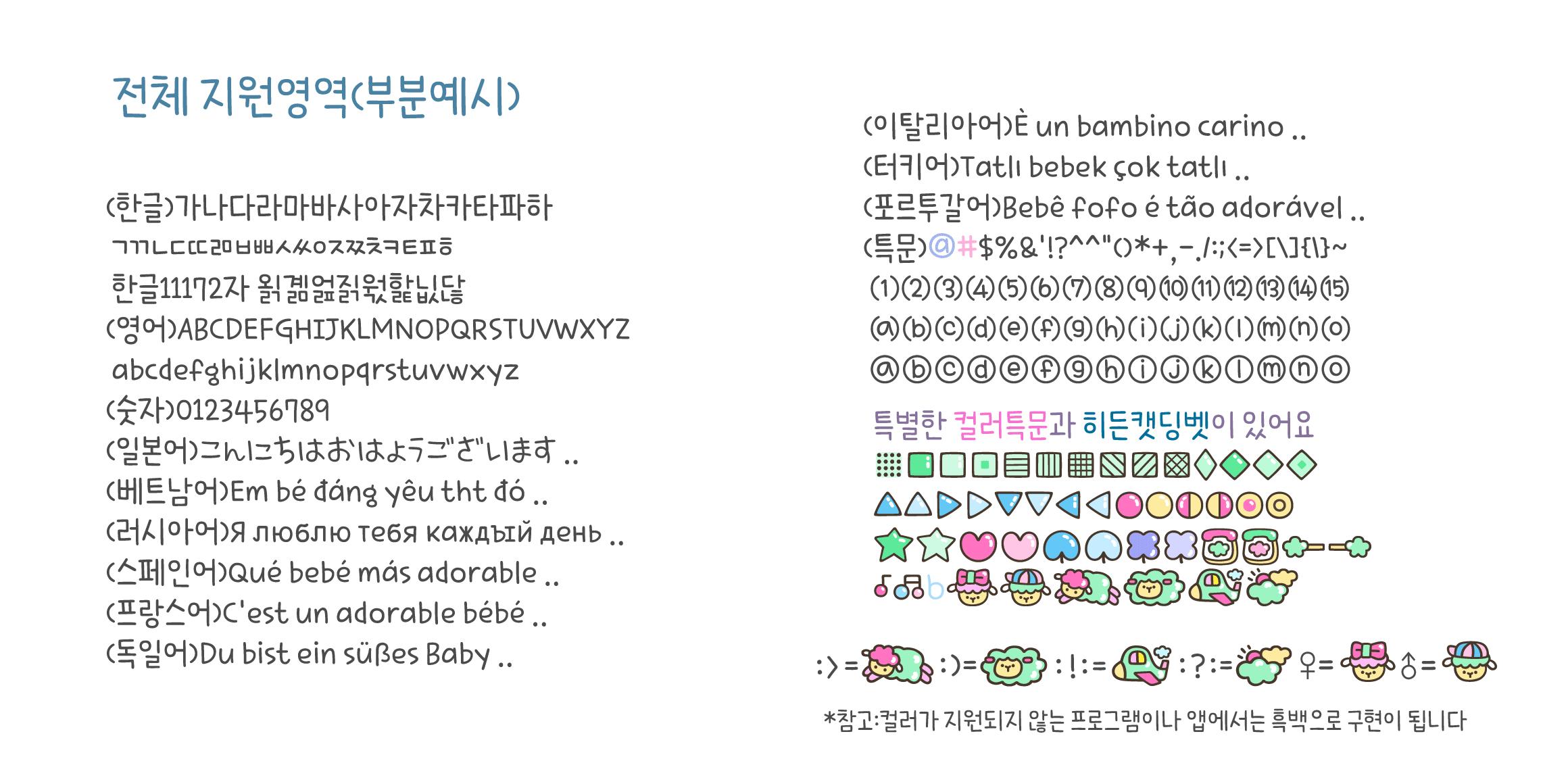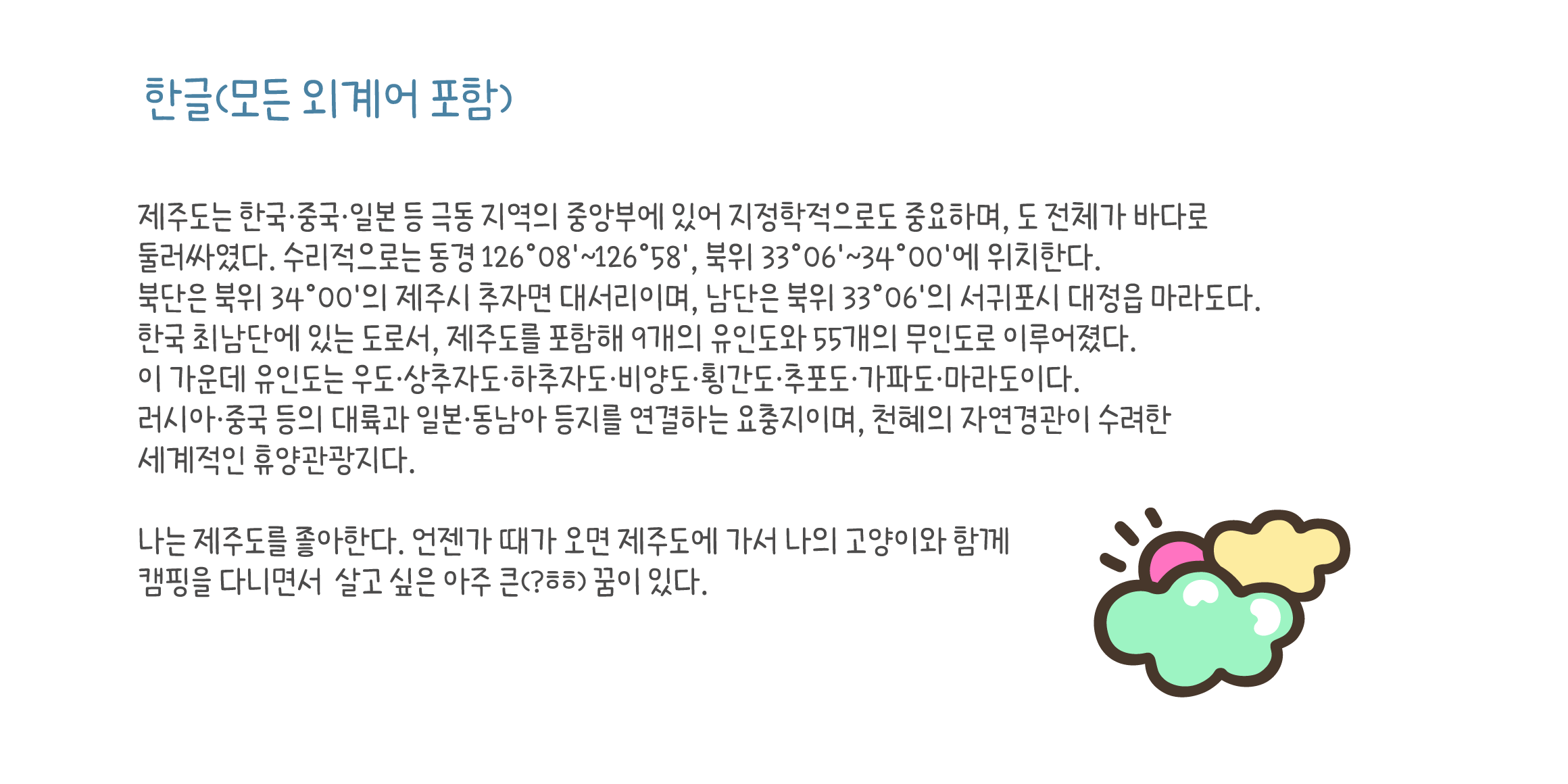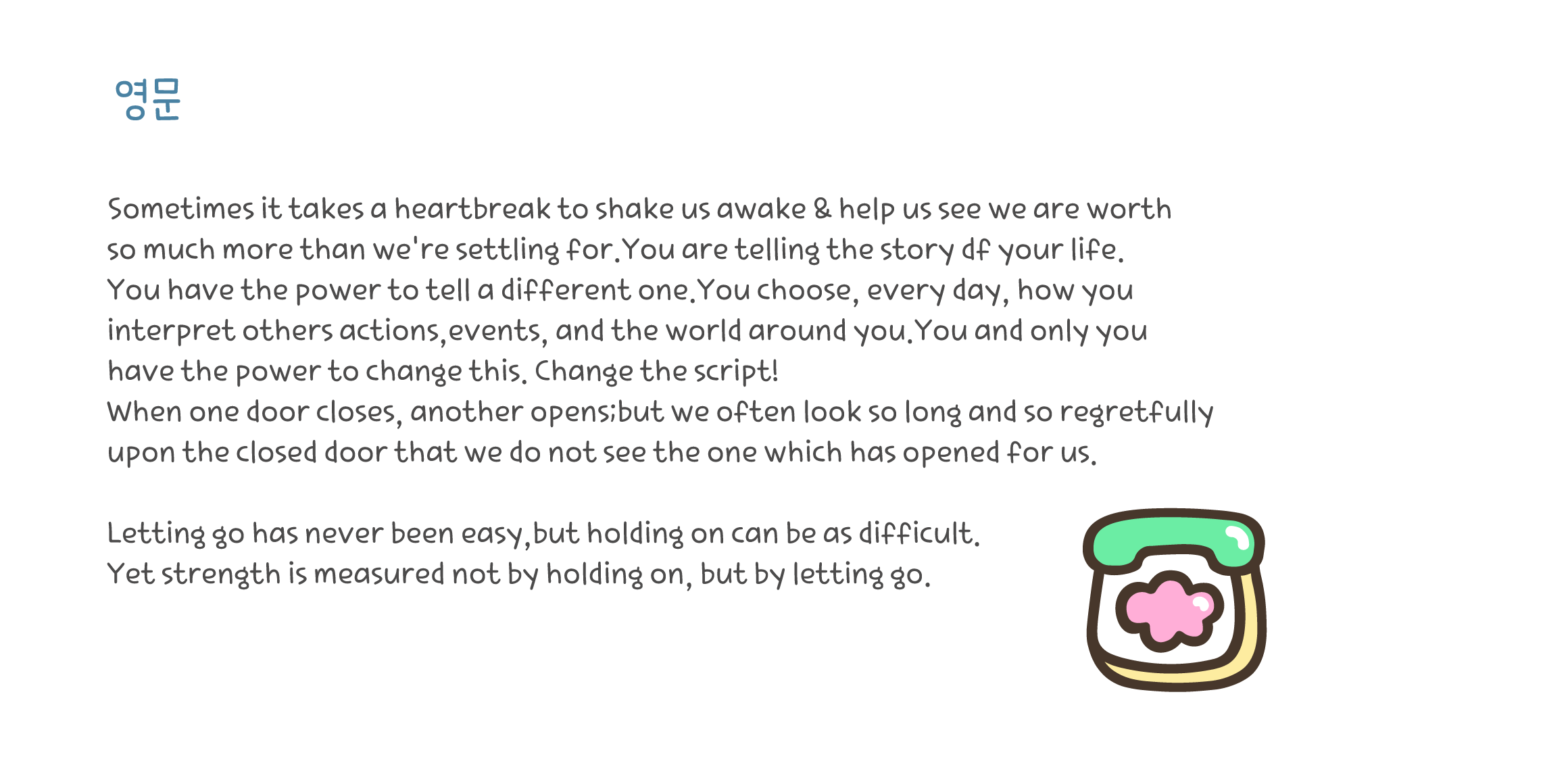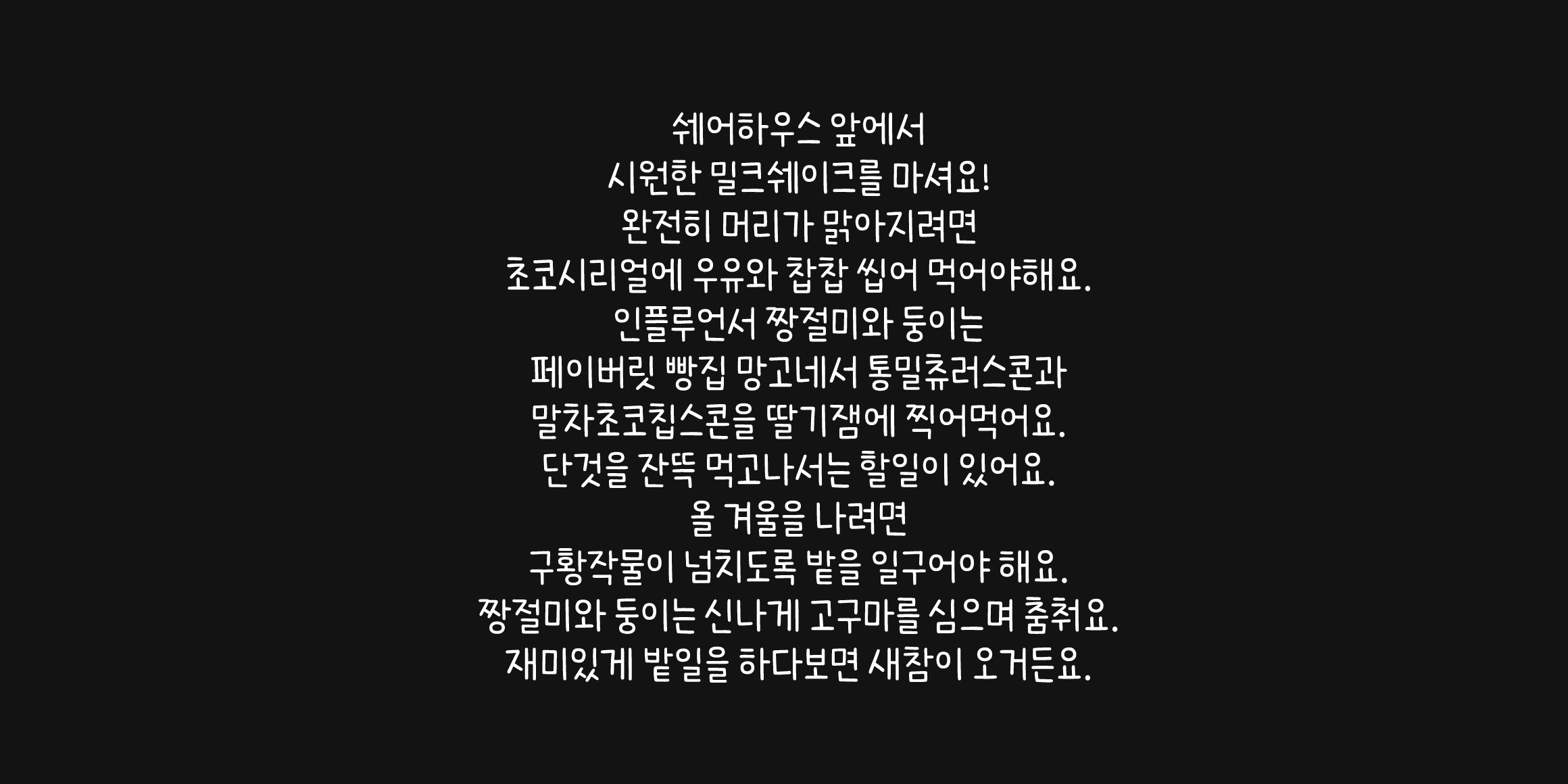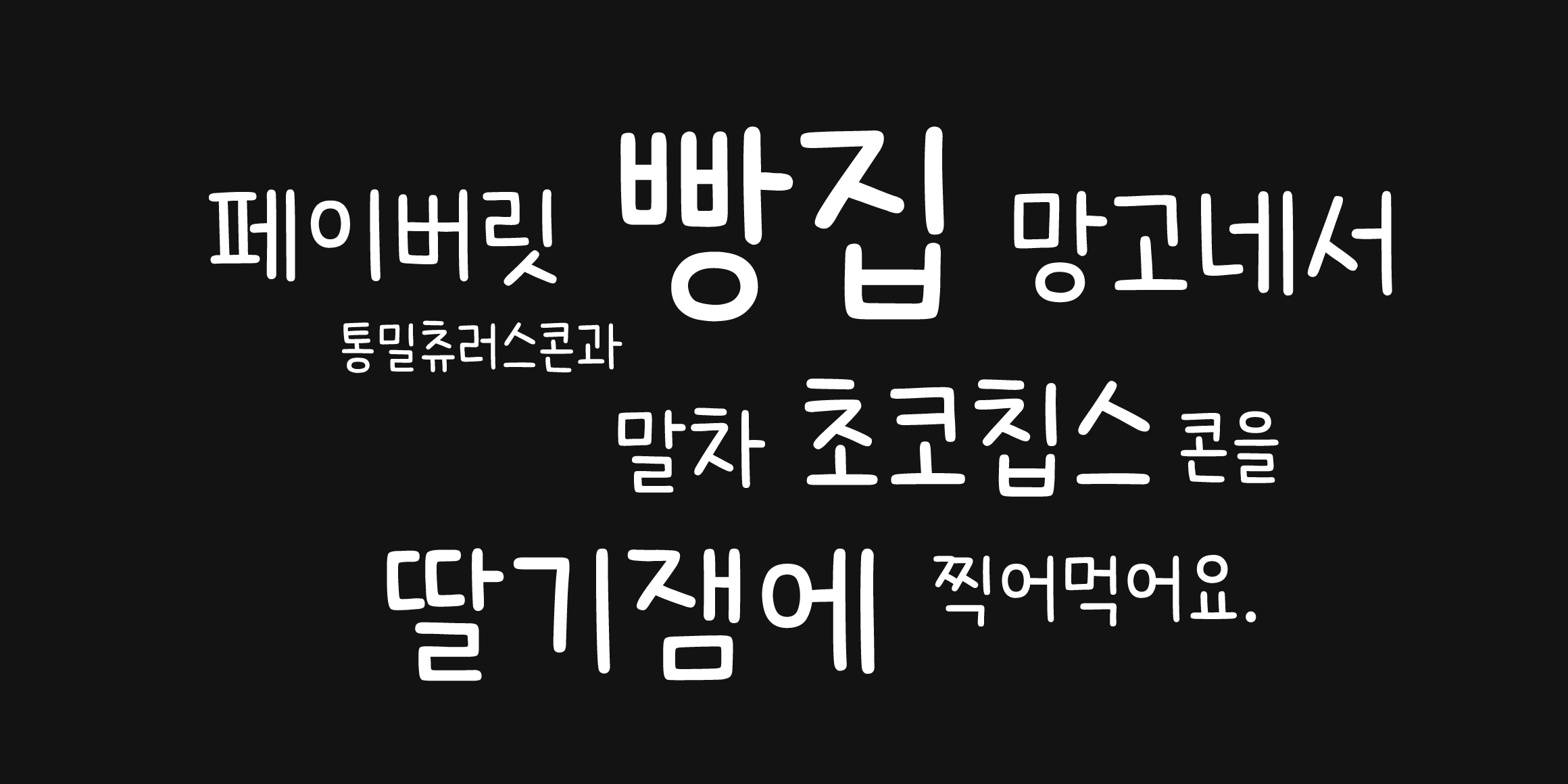
(캣폰트 시즌2 입니다)
우연히 올려다 본 하늘에
몽실몽실 양떼구름이 가득할 때 정말 기분이 좋아요!
옆을 지나는 비행기도 좋아할 것만 같은
양떼구름을 닮은 기분좋은 글꼴입니다.
♥키보드 ; > ; ) : ! : : ? : 을 연달아 치면
매력적인 캣딩벳이 나타납니다.
♥영어 일어 베트남어를 포함한
독일 프랑스 러시아 이탈리아 포르투갈 스페인 터키 등
유럽의 다양한 국가들의 언어도 함께 지원하는 등
폭넓은 언어와 특수문자 지원을 합니다.
♥캣폰트의 디자인은 오랜 시간 연구한 결과물입니다.
*컬러가 지원되지 않는 단말기나 앱이 있을 수 있습니다.
*컬러가 들어간 글자들은 두껍게(Bold)처리를 해도 두께 변화가 없습니다.
- Cat2양떼구름 / Cat2SheepCloud